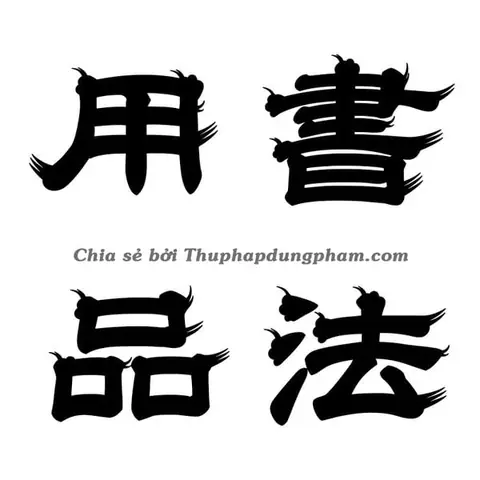
Trong thế giới thiết kế đồ họa, việc lựa chọn font chữ phù hợp có thể tạo nên sự khác biệt lớn cho tác phẩm của bạn. Đặc biệt, khi nói đến font chữ thư pháp tiếng Hoa, chúng không chỉ đơn thuần là công cụ truyền tải thông tin mà còn là nghệ thuật, là linh hồn của văn hóa phương Đông. Với hơn 100+ mẫu font chữ thư pháp tiếng Hoa đẹp nhất, bài viết này sẽ giúp bạn khám phá và tải về những bộ font chất lượng cao, hoàn toàn miễn phí để phục vụ cho các dự án thiết kế của mình.
Giới thiệu về font chữ thư pháp tiếng Hoa
Font chữ thư pháp tiếng Hoa là sự kết hợp tinh tế giữa nghệ thuật viết chữ truyền thống của Trung Hoa với công nghệ hiện đại. Những font chữ này mang trong mình vẻ đẹp cổ kính, uyển chuyển và đầy tính nghệ thuật, được tạo nên từ những nét bút lông đặc trưng. Mỗi con chữ như một tác phẩm nghệ thuật thu nhỏ, thể hiện được tinh thần và bản sắc văn hóa phương Đông.
Nguồn gốc và phát triển
Thư pháp Trung Hoa có lịch sử hàng nghìn năm, bắt nguồn từ thời nhà Thương (khoảng 1600-1046 TCN). Ban đầu, thư pháp chỉ là hình thức ghi chép trên xương thú và đồ đồng, dần dần phát triển thành nghệ thuật viết chữ với các thể chữ khác nhau như: Triện thư, Lệ thư, Khải thư, Hành thư và Thảo thư. Mỗi thể chữ mang những đặc điểm riêng biệt về cấu trúc, nét bút và phong cách.
Trong thời đại số hóa ngày nay, các nghệ nhân và nhà thiết kế đã kết hợp tinh hoa thư pháp truyền thống với công nghệ hiện đại để tạo ra những bộ font chữ thư pháp tiếng Hoa đẹp mắt, tiện dụng cho các nhu cầu thiết kế hiện đại.
Đặc điểm nhận diện
Font chữ thư pháp tiếng Hoa có những đặc điểm nhận diện riêng biệt:
- Nét bút uyển chuyển: Các nét chữ mềm mại, uốn lượn tự nhiên như được viết bằng bút lông
- Cấu trúc cân đối: Mỗi con chữ được sắp xếp hài hòa, cân đối giữa các bộ phận
- Tính biểu cảm cao: Font chữ thể hiện được cảm xúc, tâm trạng qua cách viết
- Đậm nhạt tự nhiên: Các nét chữ có độ đậm nhạt khác nhau, tạo hiệu ứng như được viết bằng mực tàu
Ứng dụng của font chữ thư pháp trong thiết kế
Font chữ thư pháp tiếng Hoa không chỉ mang giá trị nghệ thuật mà còn có nhiều ứng dụng thực tiễn trong các lĩnh vực thiết kế hiện đại. Sự kết hợp giữa truyền thống và hiện đại tạo nên những hiệu ứng thị giác độc đáo và ấn tượng.
Thiết kế logo và thương hiệu
Trong thiết kế logo, font chữ thư pháp tiếng Hoa giúp tạo nên sự khác biệt và bản sắc riêng cho thương hiệu. Những thương hiệu có yếu tố Á Đông, đặc biệt là các doanh nghiệp hoạt động trong lĩnh vực ẩm thực, văn hóa, thời trang, spa, hay các sản phẩm liên quan đến y học cổ truyền thường lựa chọn font thư pháp để thể hiện sự uy tín, truyền thống và tinh tế.
Ví dụ tiêu biểu:
- Logo các nhà hàng Trung Hoa
- Thương hiệu trà đạo
- Các spa, thẩm mỹ viện mang phong cách Á Đông
- Thương hiệu thời trang lấy cảm hứng từ văn hóa phương Đông
Thiết kế bao bì sản phẩm
Font chữ thư pháp tiếng Hoa đặc biệt phù hợp với các sản phẩm có yếu tố truyền thống, cổ điển hoặc mang tính chất thủ công. Việc sử dụng font thư pháp trên bao bì không chỉ giúp sản phẩm trở nên sang trọng, tinh tế mà còn tạo được niềm tin và sự gần gũi với người tiêu dùng.
Các loại sản phẩm phù hợp:
- Trà, cà phê đặc sản
- Mỹ phẩm thảo dược
- Thực phẩm chức năng
- Rượu, bia thủ công
- Sản phẩm thủ công mỹ nghệ
Thiết kế poster và ấn phẩm truyền thông
Trong thiết kế poster, đặc biệt là các poster sự kiện văn hóa, triển lãm nghệ thuật, hay các chương trình biểu diễn, font chữ thư pháp tiếng Hoa giúp tạo nên không khí trang trọng, nghệ thuật và đầy tính biểu cảm. Font chữ không chỉ truyền tải thông tin mà còn góp phần tạo nên phong cách, cá tính riêng cho ấn phẩm.
Ứng dụng cụ thể:
- Poster triển lãm tranh thư pháp
- Poster sự kiện văn hóa truyền thống
- Thiệp mời sang trọng
- Menu nhà hàng cao cấp
- Bìa sách, tạp chí nghệ thuật
Phân loại font chữ thư pháp tiếng Hoa
Font chữ thư pháp tiếng Hoa được phân thành nhiều loại khác nhau, mỗi loại phù hợp với từng mục đích sử dụng và phong cách thiết kế riêng. Việc hiểu rõ các loại font sẽ giúp bạn lựa chọn được kiểu chữ phù hợp nhất cho dự án của mình.